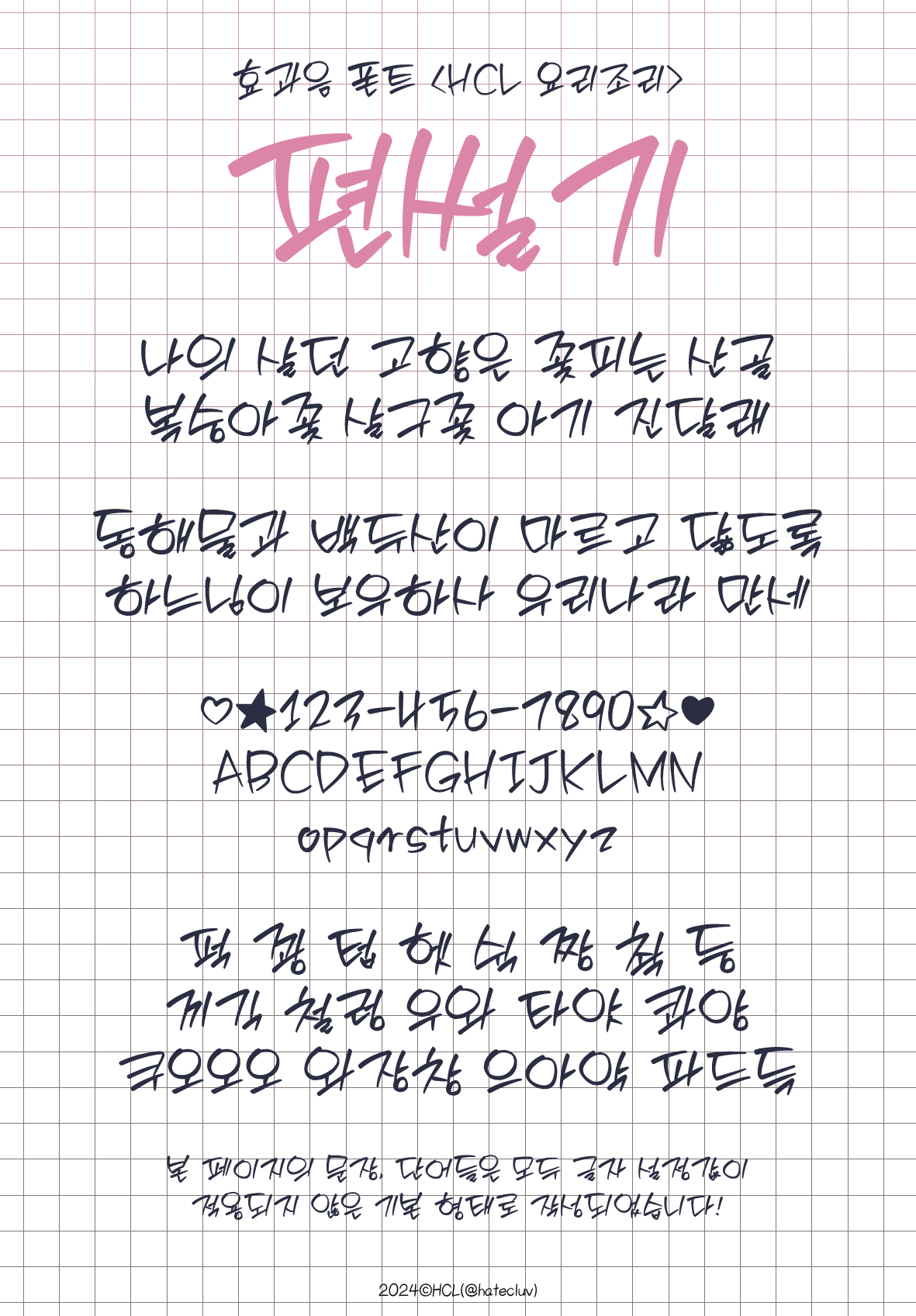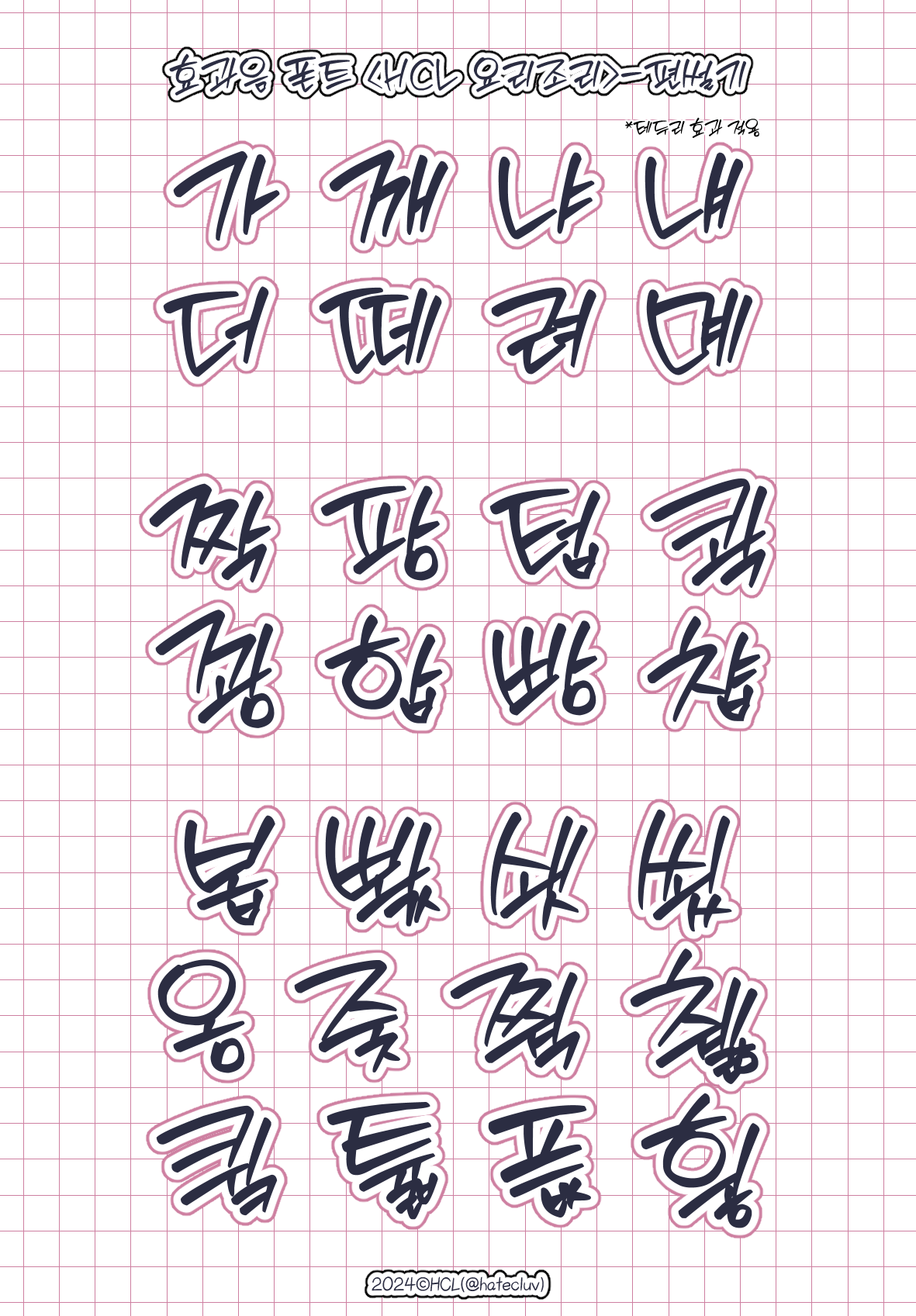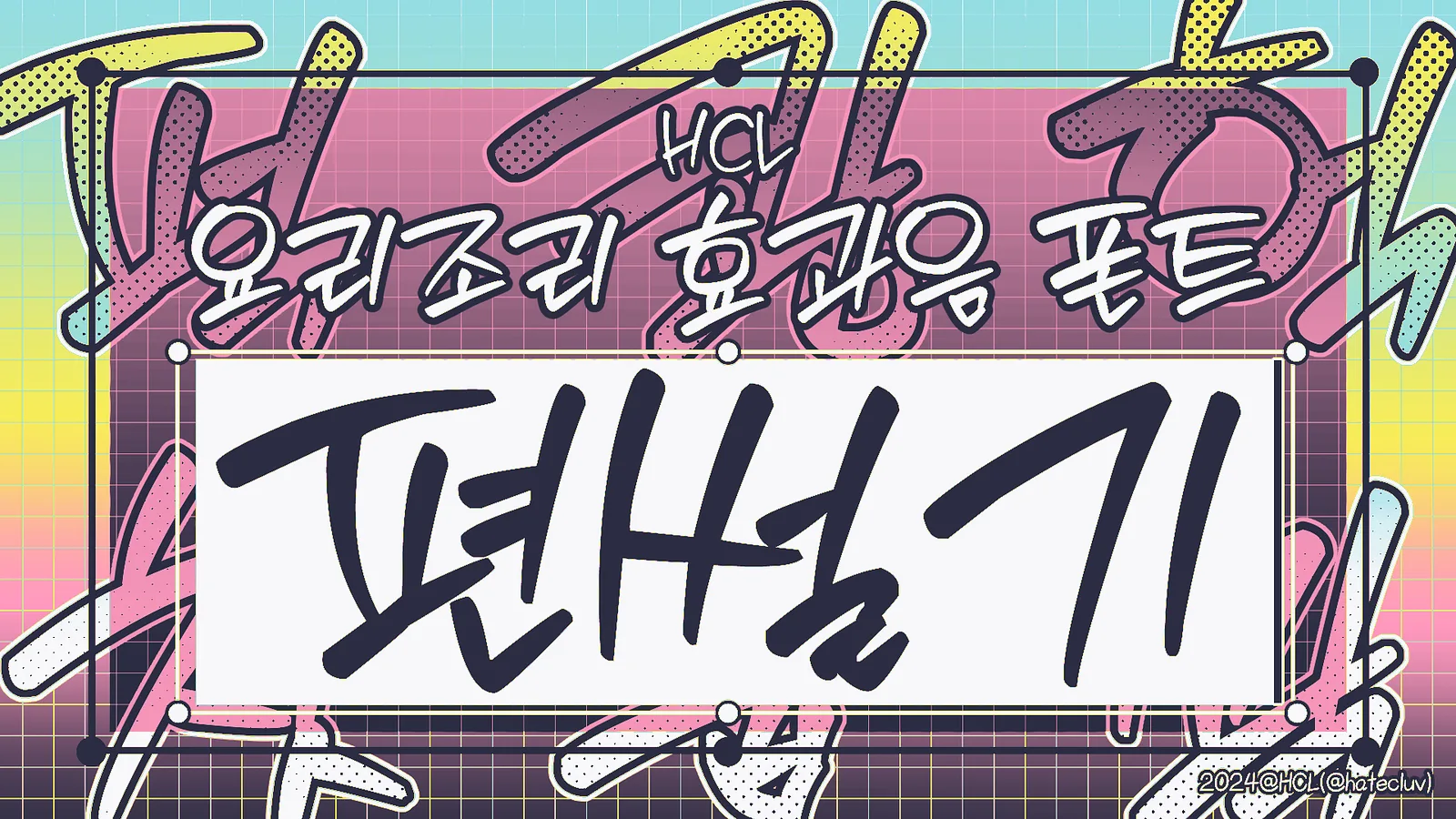
만화 효과음 느낌의 캘리그라피 폰트 5종 시리즈 <HCL 요리조리> 중 <편썰기> 입니다. 캐주얼 스타일의 웹툰 작화에 가장 범용적으로 사용할 수 있는 디자인의 글꼴입니다.
한글 조합 11172자 전체, 한글 기본 자모음(ㄱ,ㄴ,ㄷ,ㅏ,ㅑ,ㅓ...) 52자와 영문 대소문자, 숫자, 키보드 쉬프트 특수문자, ☆★♡♥, ©(카피라이트 문자) 등 추가 120글자를 지원합니다.
HCL 요리조리 편썰기